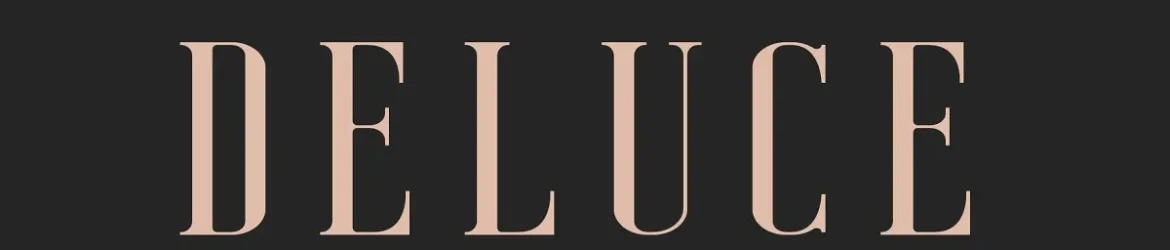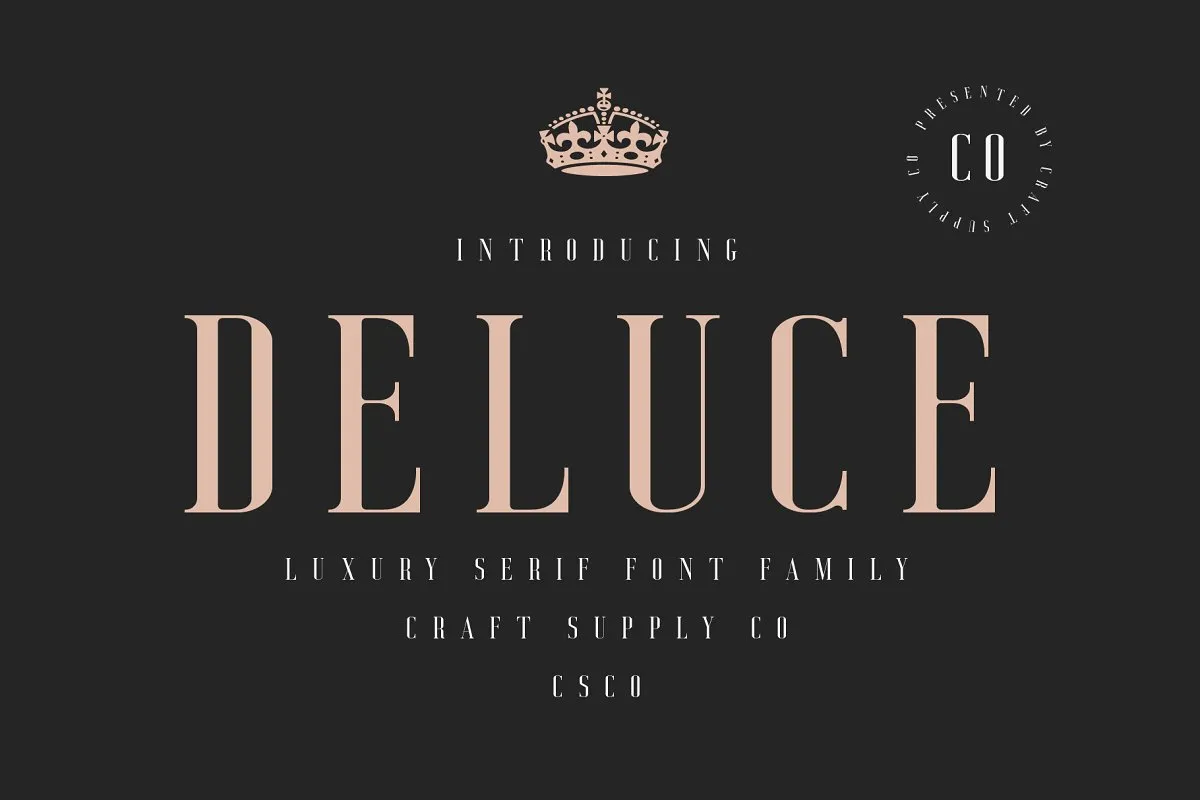
Deluce Serif Font
Olá a todos! Estou aqui uma nova opção para a sua paleta de fontes, que gostei muito e usei recentemente para um trabalho. É chamada Deluce Serif Font. Esta é uma família de tipo serif moderna e elegante, inspirada nos serifs transicionais. Uma das características mais interessantes da Deluce – Tipo Serif Luxuoso são os poucos contrastes nas linhas do texto, as formas retas dos caracteres redondos e a preservação de um ar de eficiência e profissionalismo. Com uma gama variada de estilos, esta fonte é perfeita para logotipos, cartões de visita, mensagens, posters, identidades de marca, notas pessoais, títulos de design, cabeçalhos de blog e citações artísticas ou tipográficas. Espero que você goste tanto quanto eu!